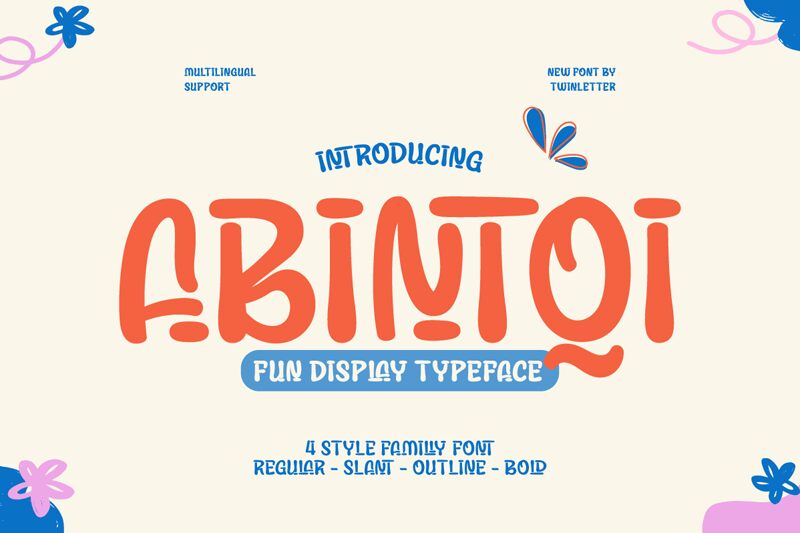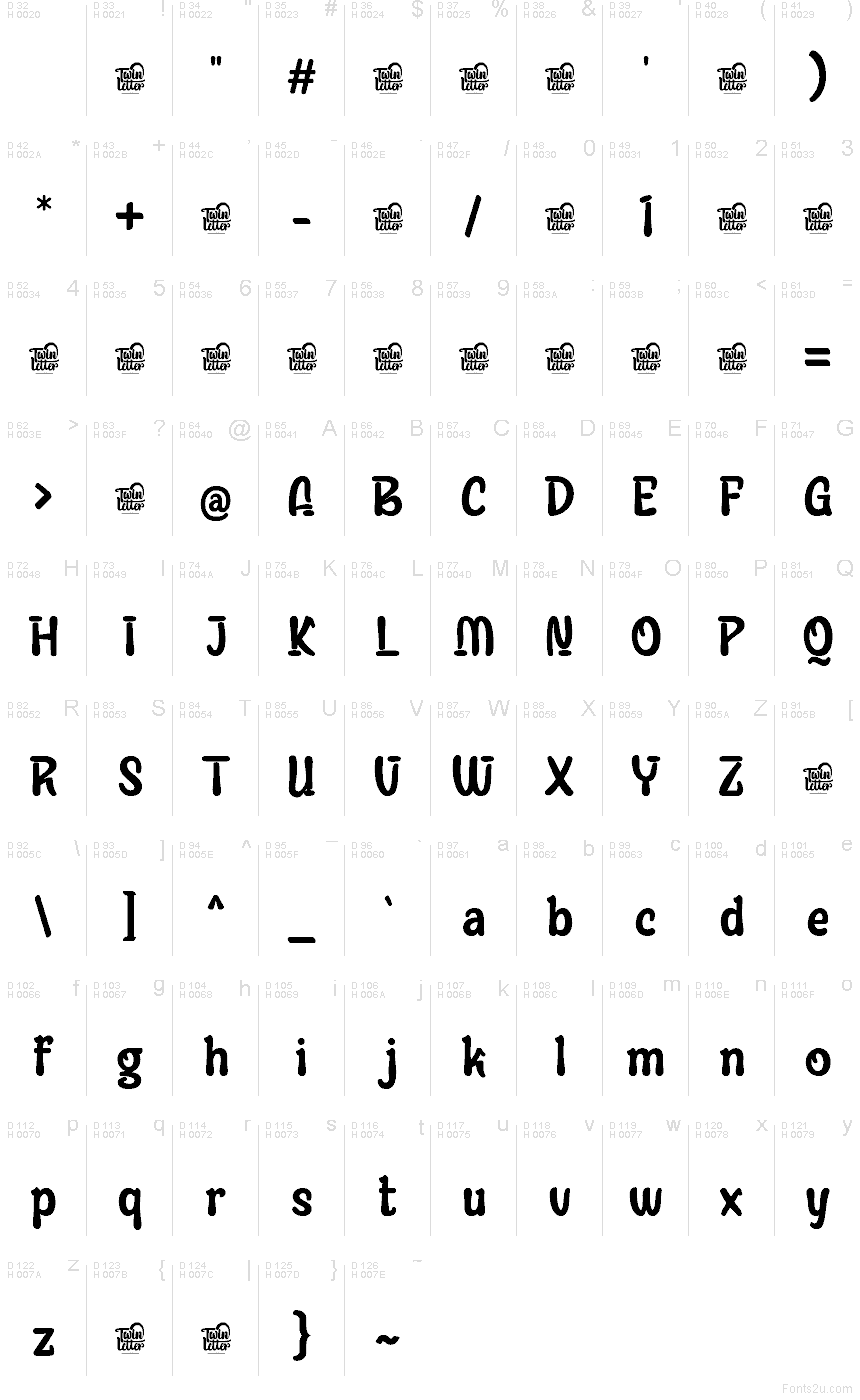
Abintqi, uma criação de Twinletter, apresenta-se como uma fonte display lúdica e dinâmica que chama a atenção pelas suas curvas marcantes e pelo design descontraído. Cada caractere transborda personalidade própria através de formas arredondadas que transmitem proximidade e criatividade. O corpo encorpado da fonte confere-lhe uma presença calorosa, tornando-a ideal para projetos gráficos que buscam ser envolventes e convidativos.
As peculiaridades encantadoras desta fonte tornam-na perfeita para trabalhos que pedem um toque de diversão, como livros infantis, identidades visuais descontraídas ou peças publicitárias criativas nas quais a distinção é essencial. O estilo inconfundível de Abintqi garante que qualquer composição ganhe destaque com leveza e originalidade.